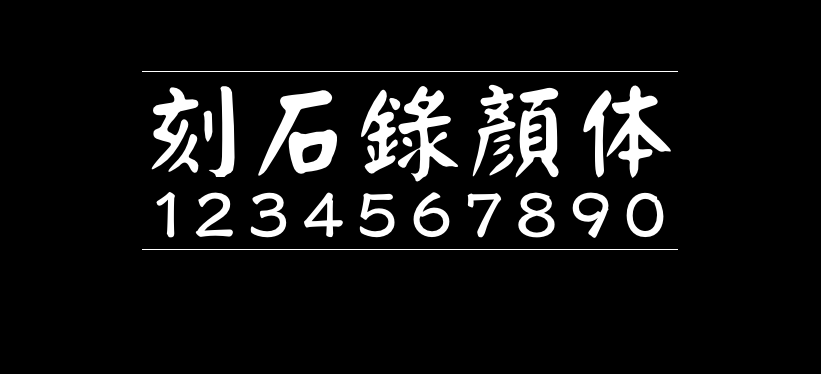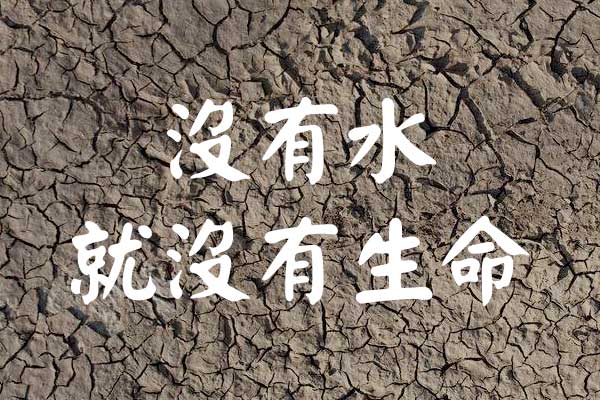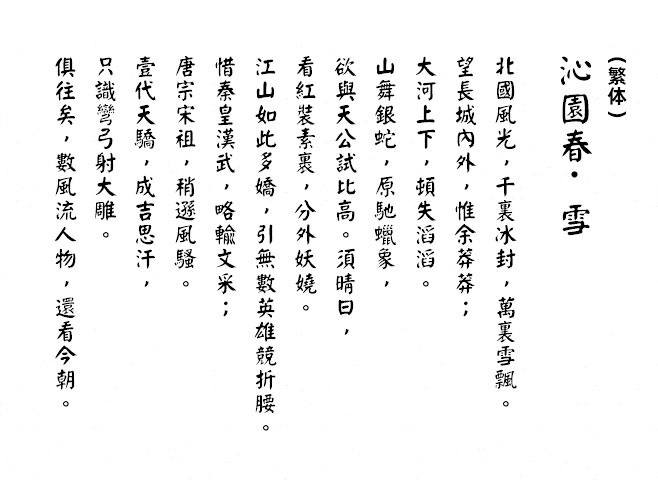
刻石录颜体
刻石录颜体(I.Ngaan)是一款基于台湾王汉宗颜体修改而成的颜体楷书,重新制作和修整原字型中缺少的或有欠美观的部份,例如全半形英数、平假名、片假名、拉丁字母、俄文字母、阿拉伯数字、圈圈字、常用符号等。该字体主要为繁体,简体文字会相对少些。
至于对汉字部份的修改,不外乎两种工作:一、改变字形写法,二、增補缺字。
改变字形者,把字型中一些从俗的写法,改为正统的字样。
例如:「青」字下方本从「円」,即「丹」;「聰」字本从「囪」,而非「囱」;「氐」字末笔为橫,不是点等。然而,由于颜体乃由毛笔楷书字体发展而來,属手写字型,因此也接受一些手书写法,如「羽」字撇笔写作「点、挑」;「糹」旁下方作三点;「飠」旁也不改作「?」等。補字者,则增造常用香港外字表中的字。
目前中文开源字体尚少,犹幸还有一些有心人士,就如王汉宗教授。王教授乃台湾中原大学数学系教授,当年天蚕中文字库正由他硏发。他先后在2000年和2004年,捐出共42套字型作开源使用,全部均以开源协议GNU GPL分发。
可惜于2005年,文鼎公司认为王教授的部份字型与它们的商业字型有形似的争议。爲了避免法律纠纷,各开源网站都把王教授的字型下架。而所谓的法律纠纷,至今并无公开的结果。